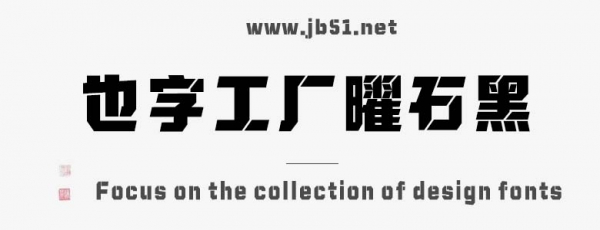
也字工廠曜石黑是由也字工廠出品的藝術(shù)字體 ,字體筆觸略粗粗實(shí),字形端正,具有很好的視覺(jué)感,適合應(yīng)用于藝術(shù)設(shè)計(jì)、平面宣傳設(shè)計(jì)、網(wǎng)頁(yè)設(shè)計(jì),書(shū)法字帖等領(lǐng)域。有需要的朋友快來(lái)本站下載使用吧。